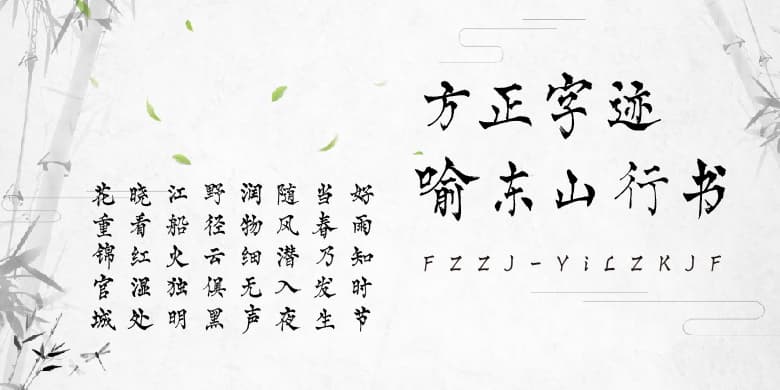
方正字迹-喻东山行书
品牌:方正字迹设计师:喻东山发行时间:2020字库编码:简繁扩展(GBK)、大陆简体(GB2312-80)分类:常规书写·毛笔字体属性:精品字
该字体有柳体的秀逸,颜体的弹性,褚体的纤细,欧体的挺拔,严肃之中,又有灵动之气,不脱廊庙风范。其笔也劲,其行也速,其撇如柳,其捺如钢,其形也矩,其态也庄。如周亚夫披甲谒君,拟关云长立玄德身旁,壮而有礼,威而不武。适用于店家招牌、匾额、广告、海报、影视字幕等。